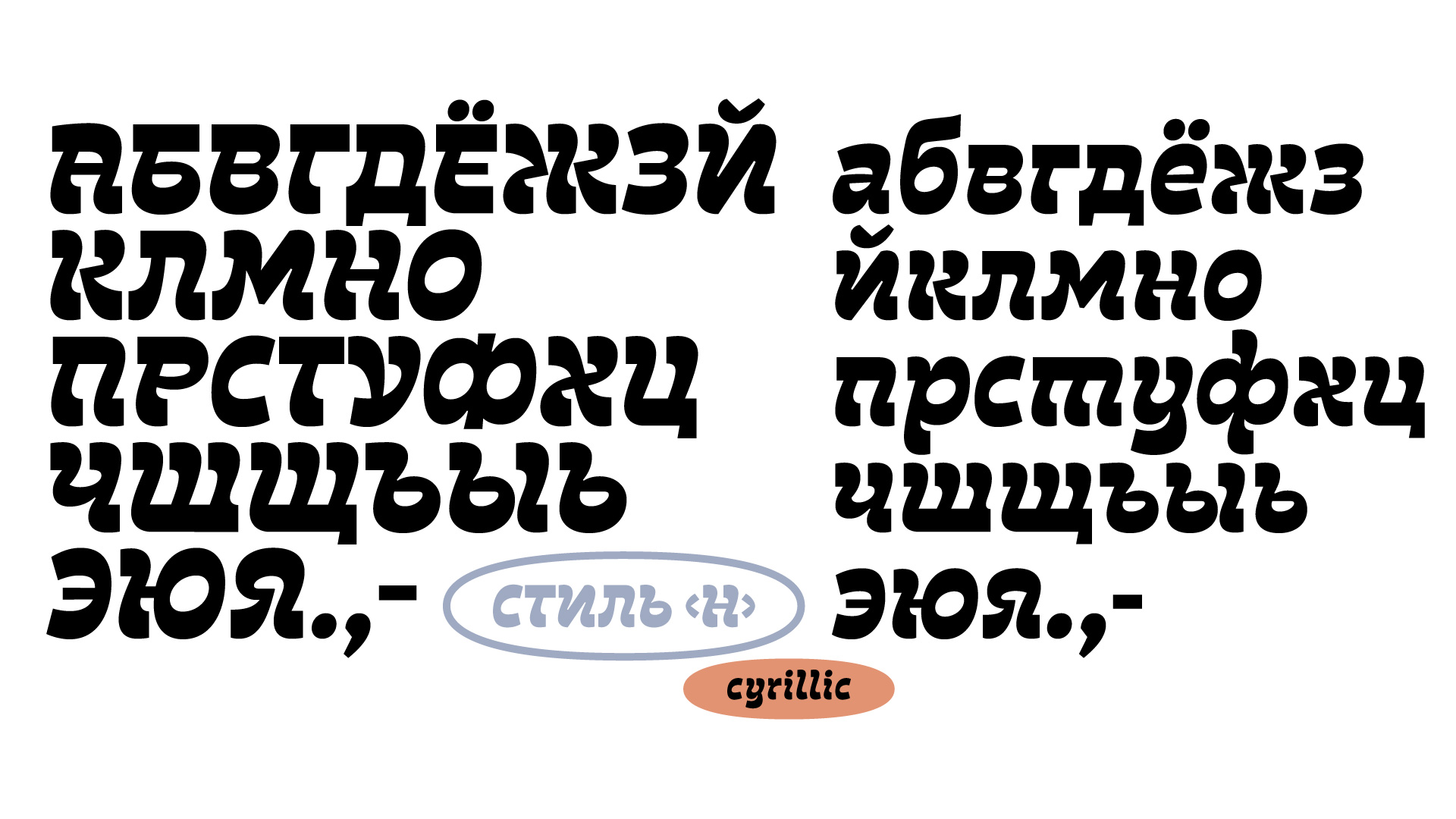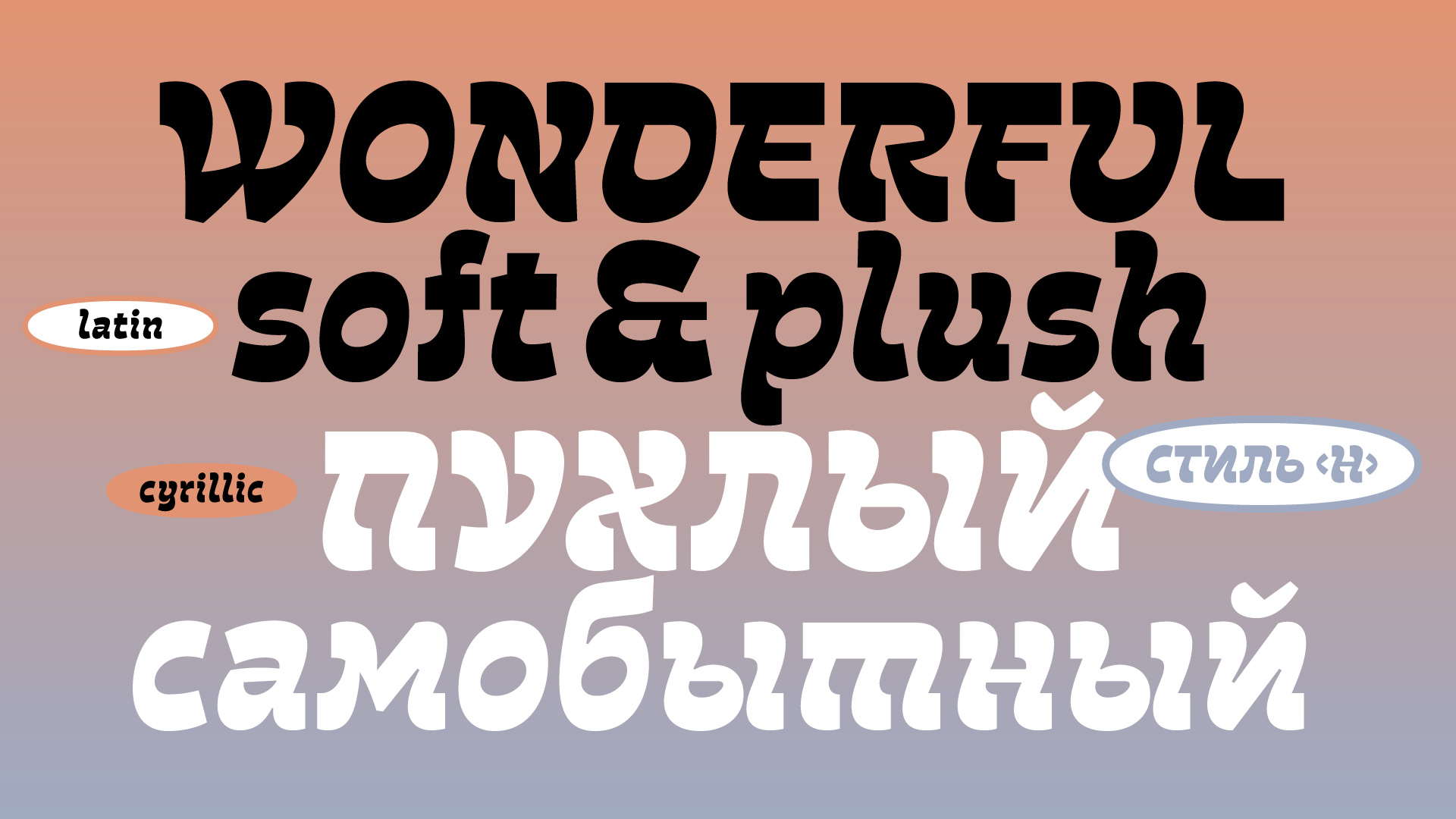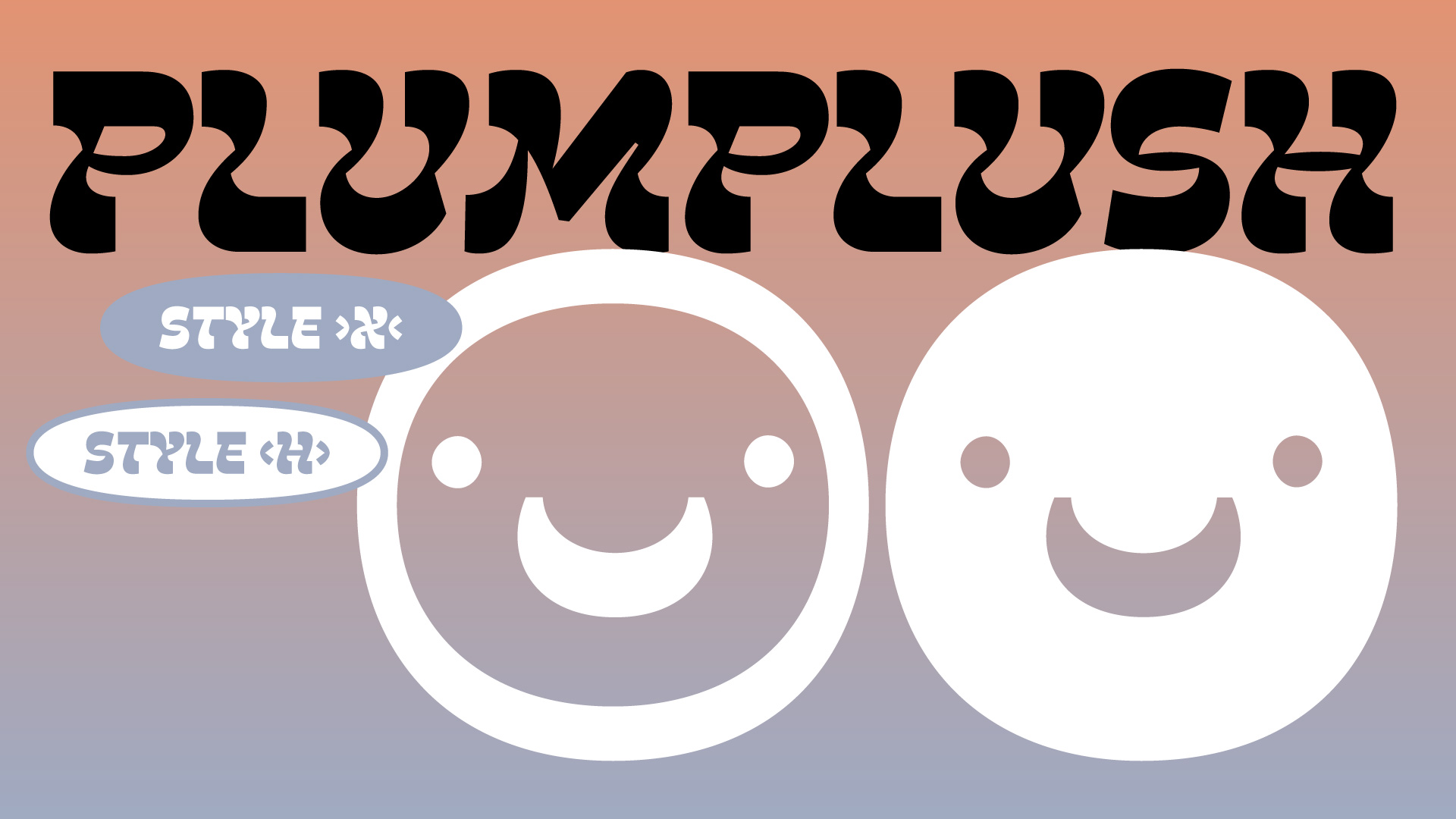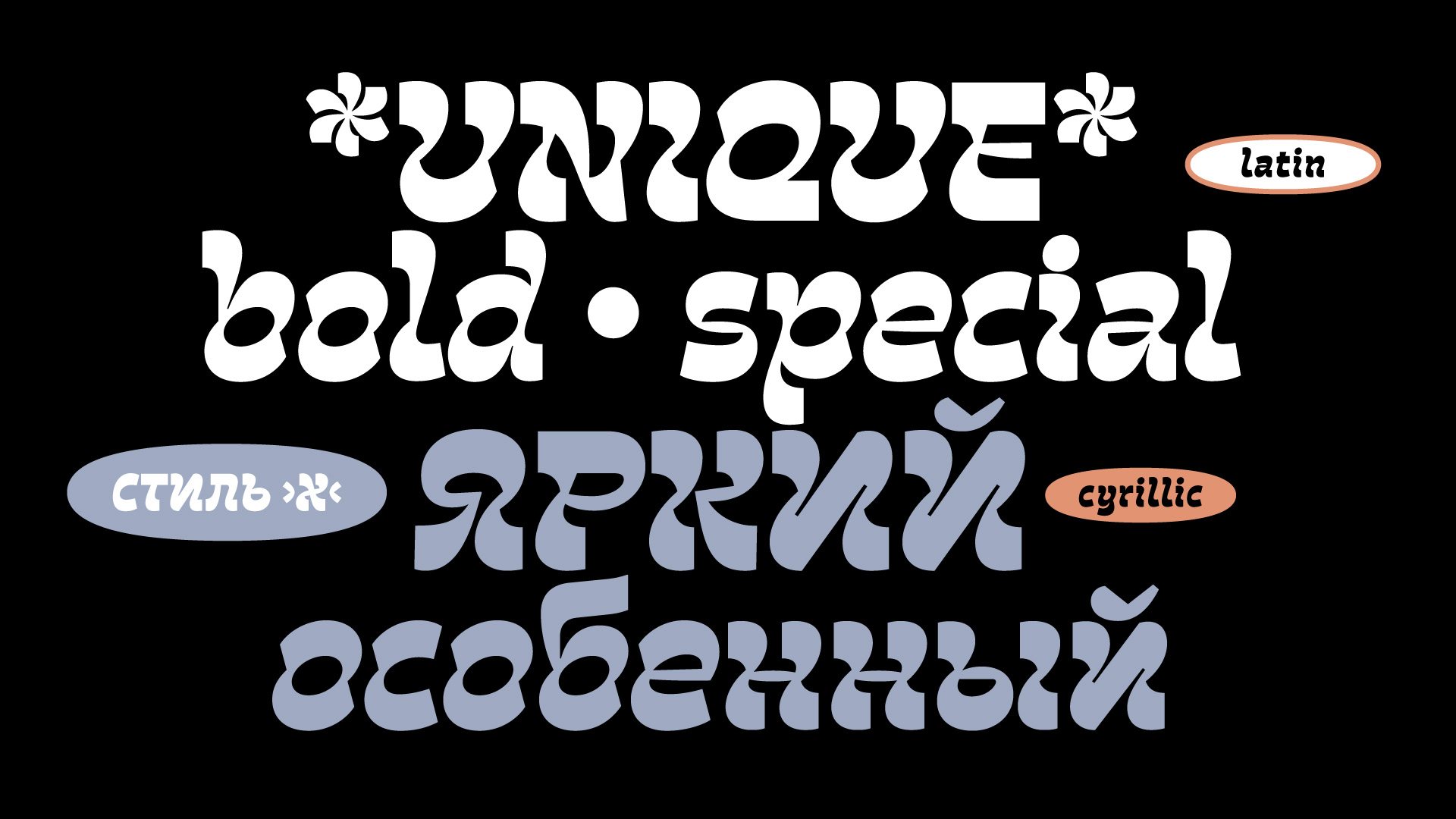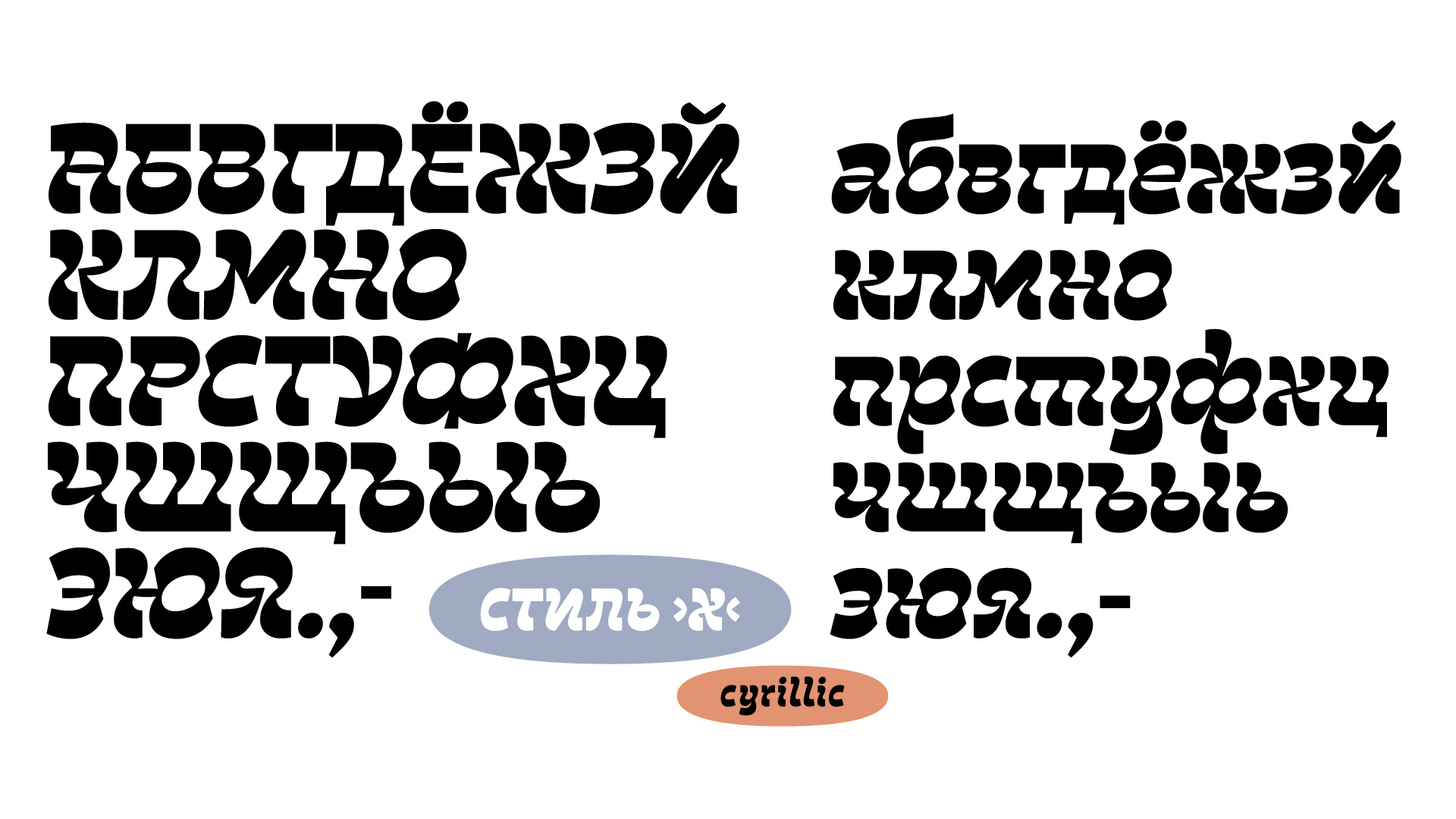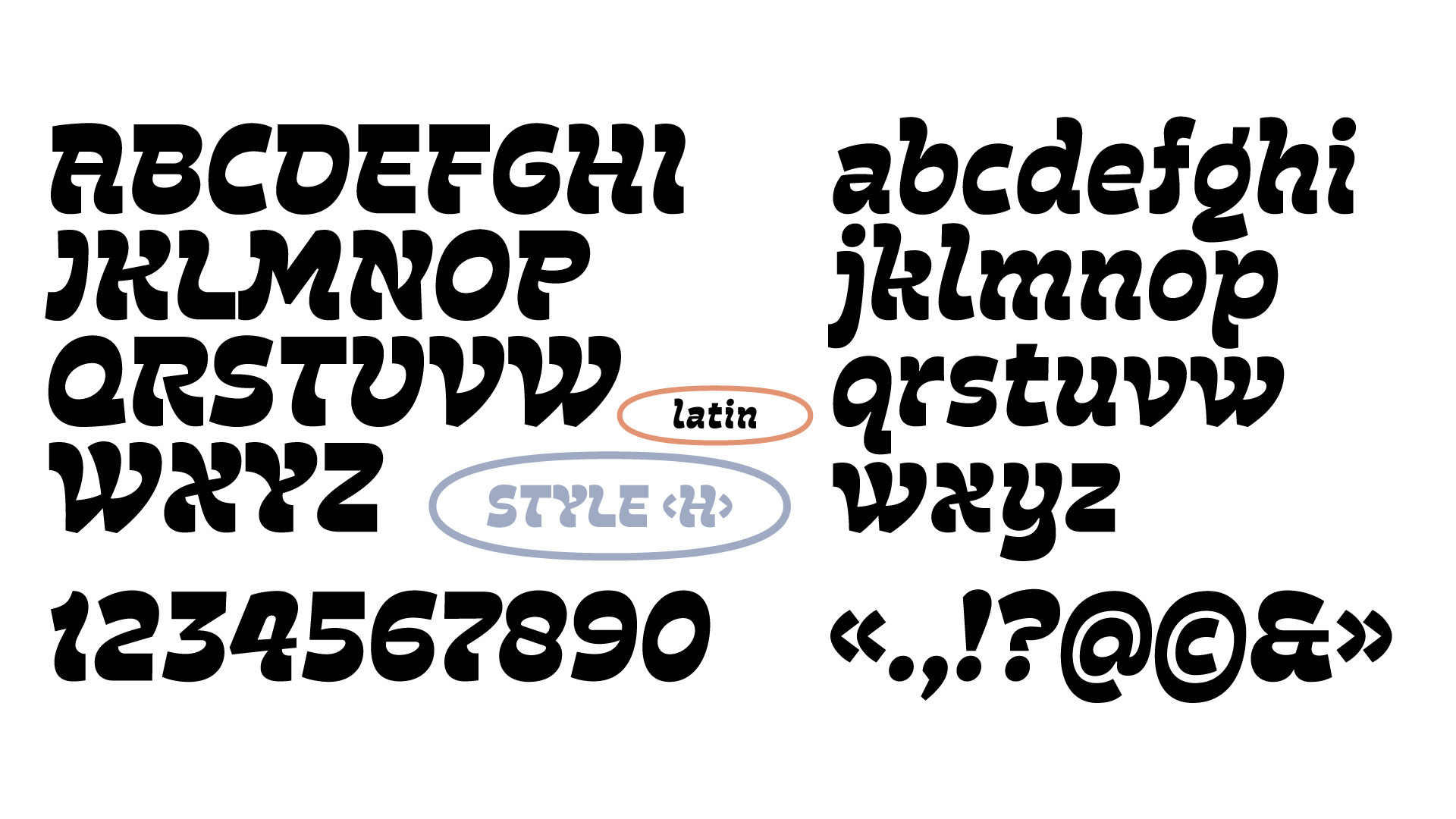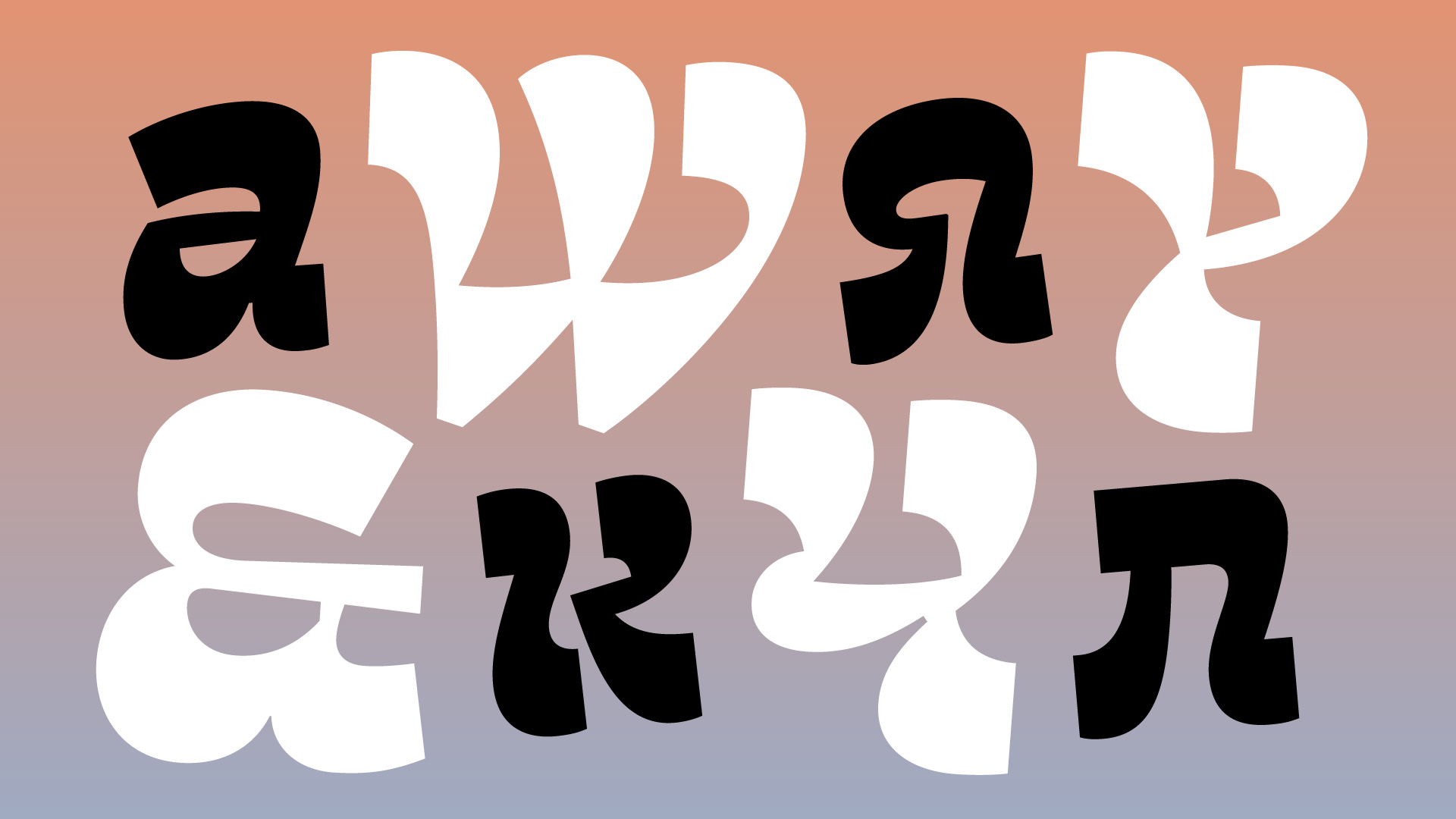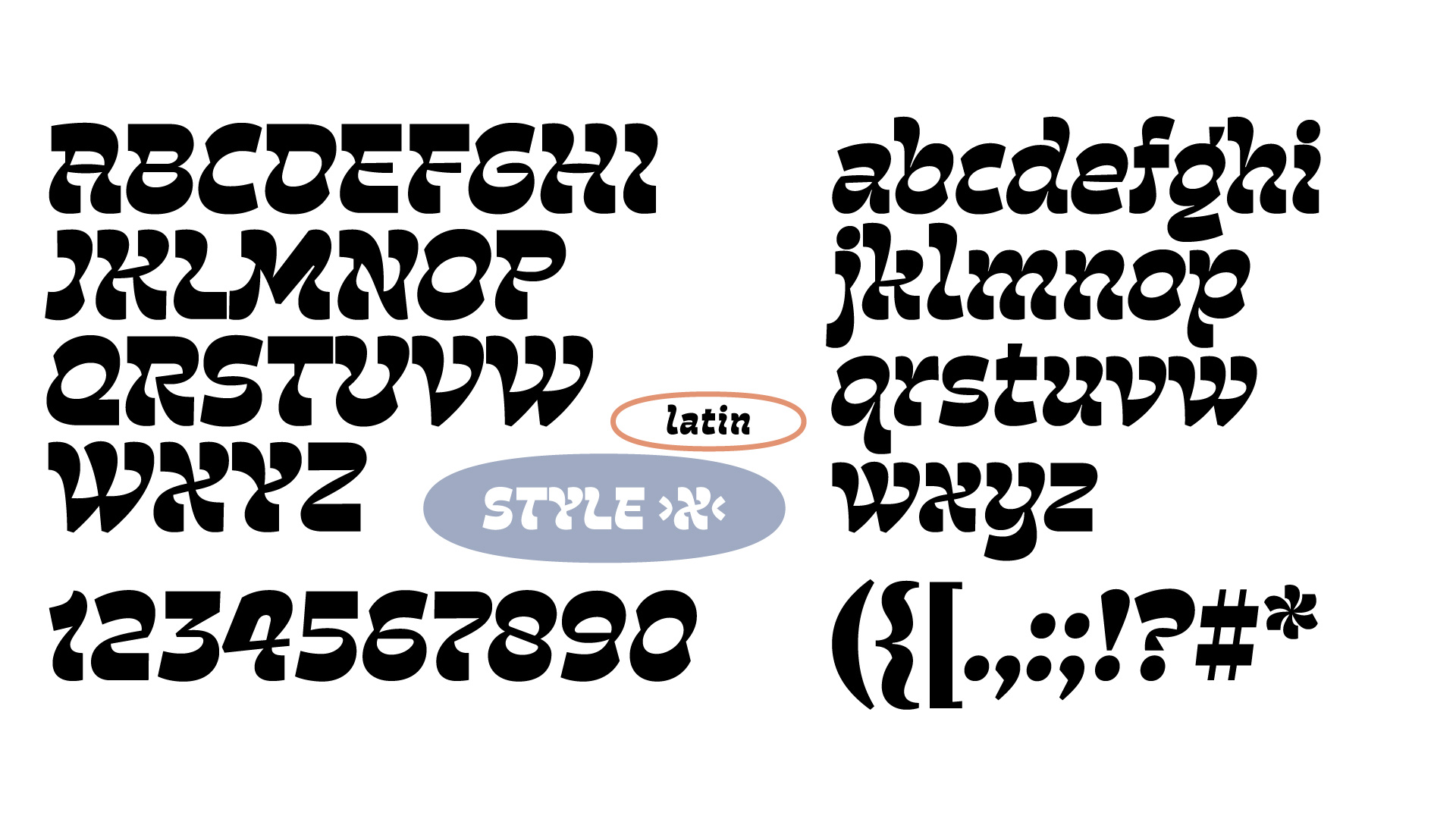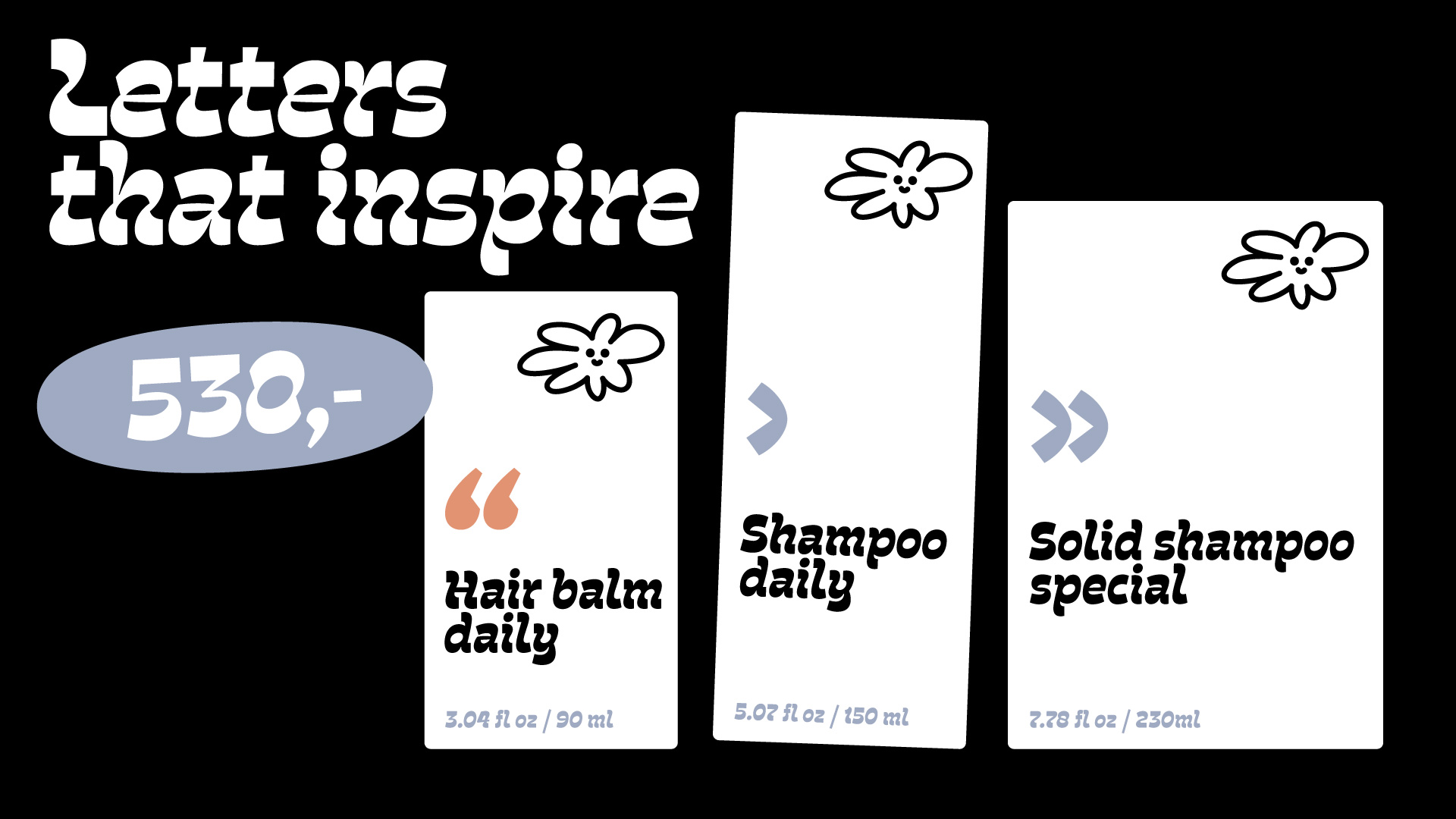
PLUMPLUSH
Plumplush начался с половинки знака -i-, который я вытащила из логотипа и буква -о- вначале напоминала сливу с косточкой внутри. Отсюда и название. Буквы строились из элементов отраженных относительно горизонтали, поэтому появилась перетяжка посередине — талия. У всех букв она расположена на одной высоте.
Буквы, опираясь на гуманистический минускул, полностью нарисованы. Логика плоского инструмента прослеживается, написать так от руки возможно только в своем воображении. Plumplush — шрифт с обратным контрастом, несимметричными односторонними засечками и варьирующимися углами концевых элементов.
Сейчас Plumplush это два шрифта: Style X и Style Н, — с разницей в талии и степени акциденции. Style X для крупного кегля выше 48 pt. Его можно назвать шрифтом «от кутюр», потому что он производит впечатление. Второй, Style Н — как «пред-а-порте» или готовое платье для книги, периодики и упаковки. Хорошо сработает и в крупном кегле и небольшом абзаце от 24 pt.